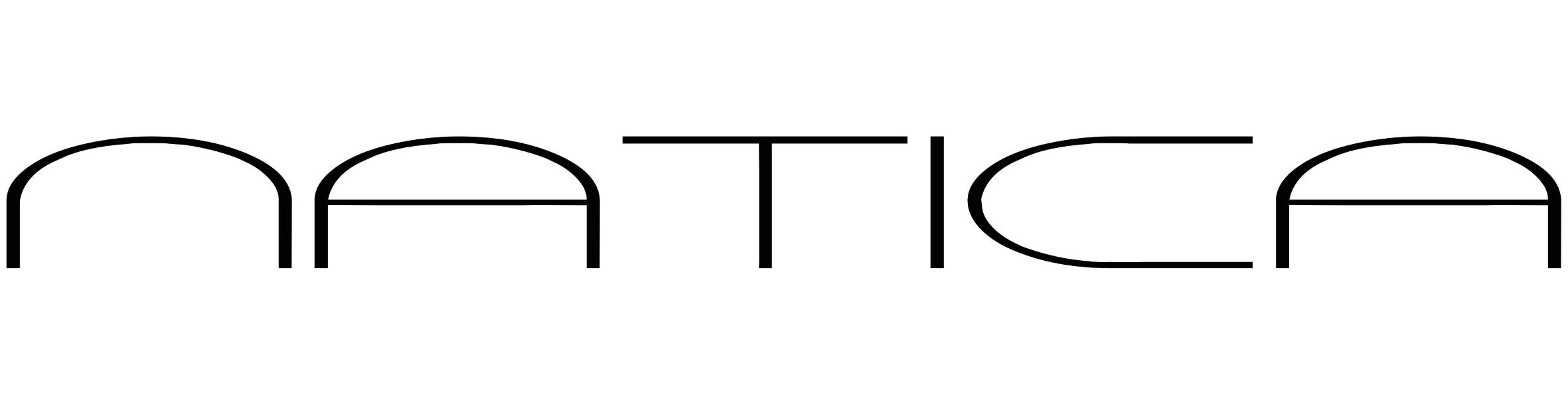
Welche Schrift? Natica
Hallo Leute, ich habe die Datei selbst vor 4 Jahren erstellt und leider den Namen der Schrift nicht aufgeschrieben. Ich kann mich lediglich erinnern dass es eine Kombination aus Klein-und Großbuchstaben ist. Vielen Dank im voraus.
Ich habe das Bild einfach mal Whatsfontsis zum Fraß vorgeworfen, mit der Vermutung, dass diese Schrift extrem in die Breite gezogen wurde.
Gleich das erste Ergebnis sieht sehr vielversprechend aus. Der Kandidat heißt We 2000: